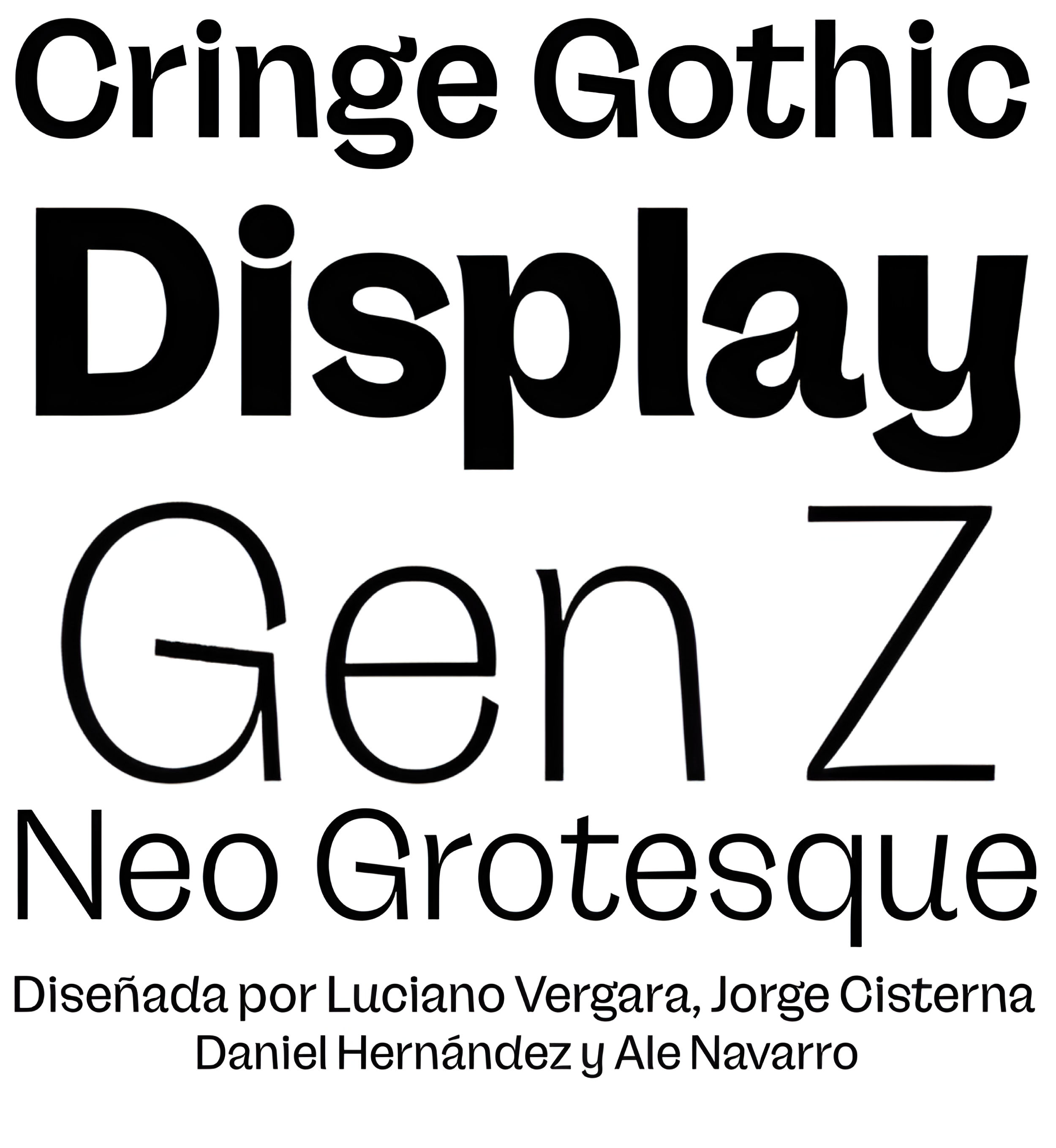
Cringe Gothic
Créditos Luciano Vergara, Jorge Cisterna, Daniel Hernández, Ale Navarro
Descripción
Una grotesca con un guiño, no una mueca.
Cringe Gothic no rehúye la incomodidad, sino que se deja llevar por ella. Con curvas que coquetean con la torpeza intencionada y terminales que desafían la lógica tipográfica, esta grotesca sans se siente como una sonrisa inoportuna: incómoda, entrañable y un poco absurda. Pero bajo su superficie poco convencional se esconde un diseño sólido, compacto y sorprendentemente versátil.
Creada para una era en la que la perfección resulta sospechosa, Cringe Gothic está pensada para marcas que prefieren parecer vulnerables a perfectas. Con ocho pesos, de Light a Extra Black, funciona con titulares que exigen presencia y con sistemas de diseño que necesitan una voz juguetona pero atrevida.
Sus formas exageradas, grandes aperturas y detalles que parecen sacados de un meme viral lo convierten en un manifiesto visual de la estética postcrítica: un estilo que adopta lo extraño, lo emocional y lo disparatado como un nuevo tipo de honestidad en la creación de marcas.
Clasificación Títulos, Dingbats
Familia(s) Cringe Gothic
Estilos 8